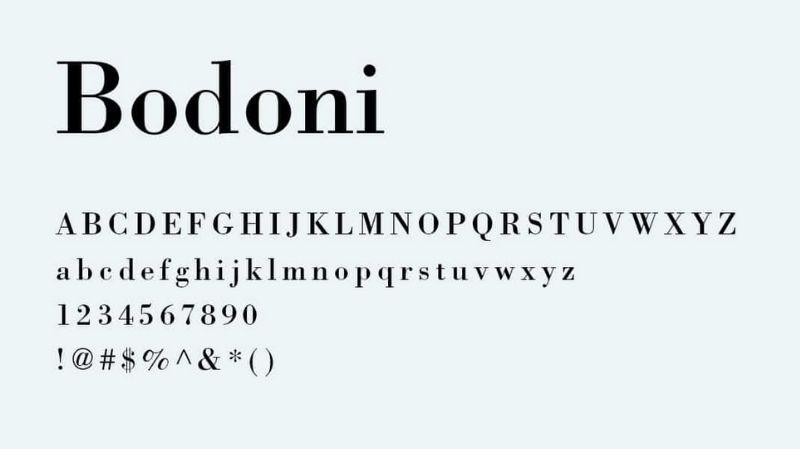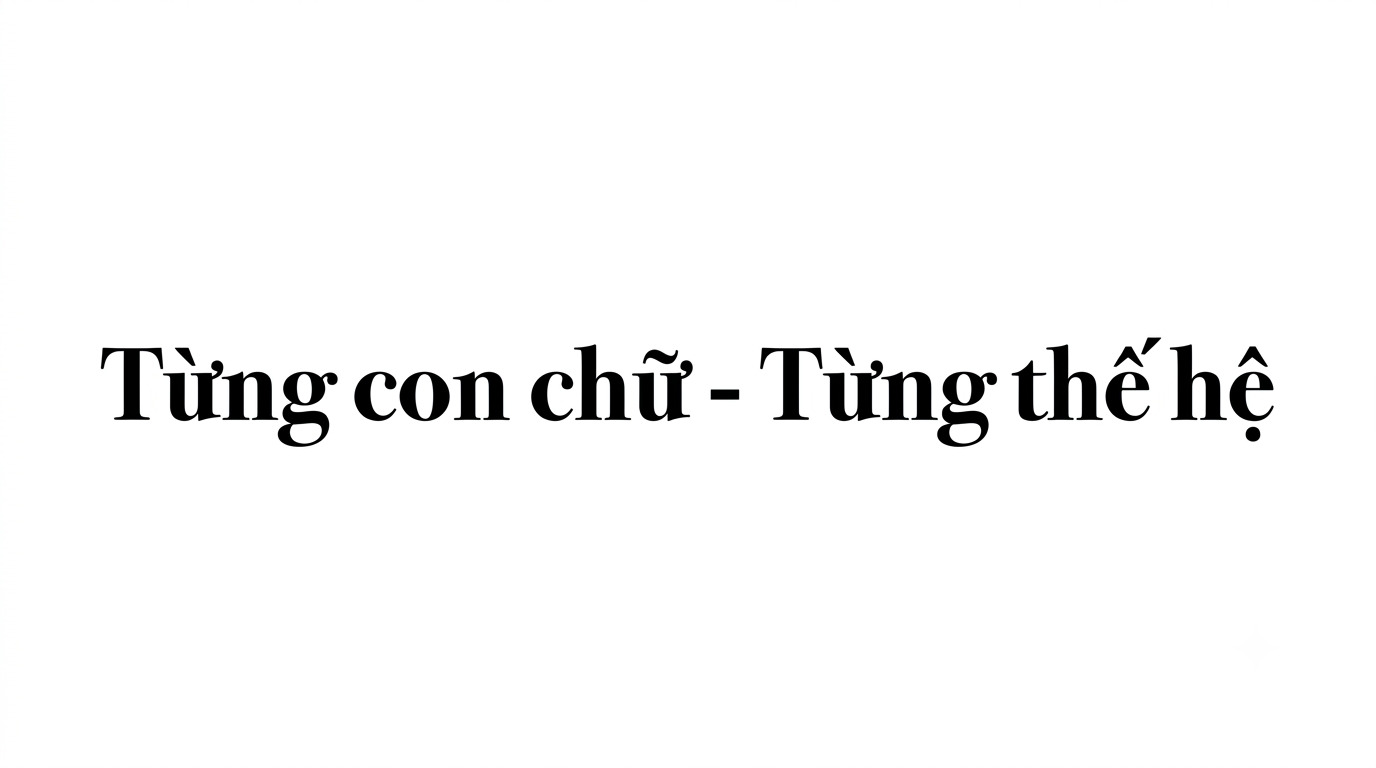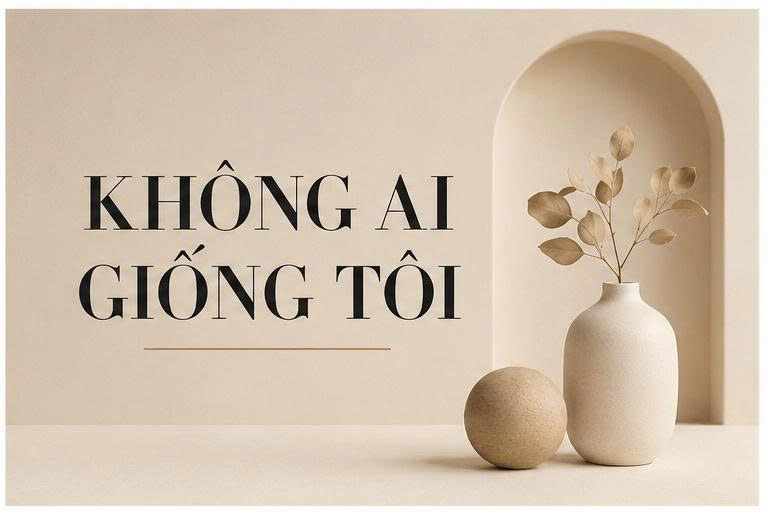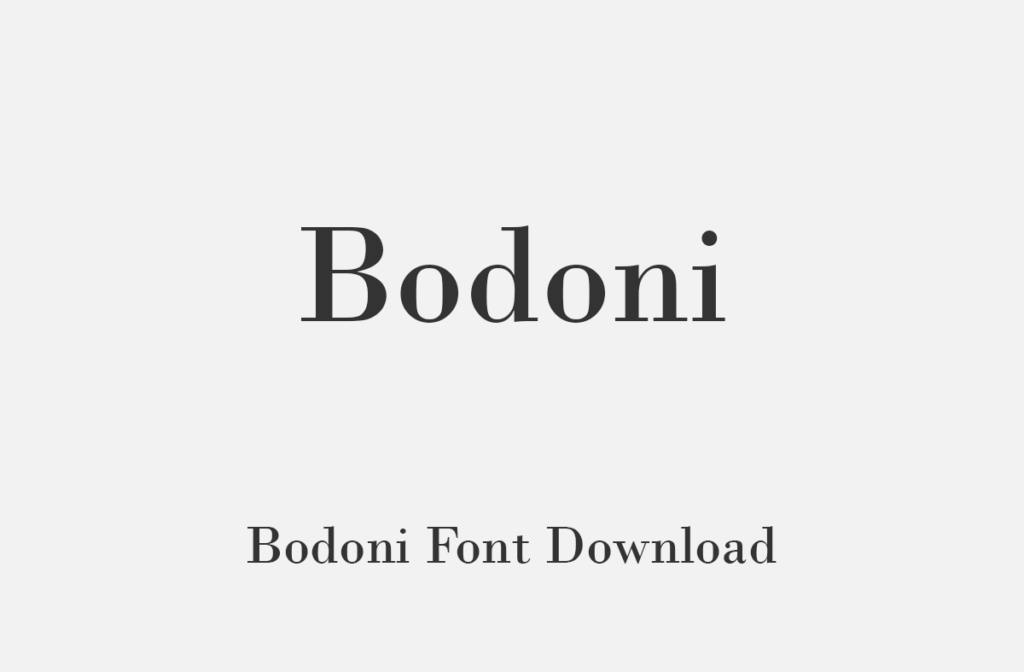
Font Bodoni Việt hóa là bộ phông chữ thuộc dòng Didone Modern Serif kinh điển do nghệ nhân in ấn Giambattista Bodoni sáng tạo tại Ý vào cuối thế kỷ 18, nổi danh toàn cầu với sự tương phản kịch tính giữa các thân chữ dày đậm và đường chân chữ mỏng manh như lưỡi dao cạo. Mang vẻ ngoài vương giả, uy nghiêm và đượm chất thời trang cao cấp, bộ font Bodoni Việt hóa là chất liệu trực quan tuyệt vời để các kiến trúc sư, nhà thiết kế kiến tạo phong thái sang trọng cho các bản vẽ phối cảnh biệt thự nghỉ dưỡng, sảnh đón tiếp khách sạn boutique hay bìa hồ sơ năng lực dự án.
Tỷ lệ tương phản cực độ và cấu trúc hình học của font Bodoni Việt hóa
Điểm cuốn hút của font Bodoni Việt hóa nằm ở cấu trúc hình học đứng thẳng tắp, các đường chân chữ nằm ngang phẳng lì không có góc bo chuyển tiếp (unbracketed serifs), tạo nên một hiệu ứng thị giác dứt khoát và thời thượng. Từng con chữ sở hữu những điểm nhấn hình giọt lệ tròn trịa ở các ký tự như ‘a’, ‘c’, ‘r’, tạo nên sự hòa quyện hoàn hảo giữa tính kỷ luật cơ học và nét duyên dáng tao nhã.
Sự ổn định về mặt thị giác của dòng font này tạo nên phong thái trang nhã, tin cậy và khẳng định vị thế đĩnh đạc của đơn vị kiến tạo. Khi xuất hiện trên các bề mặt vật liệu kiến trúc sang trọng như đá cẩm thạch trắng vân mây, inox mạ vàng xước mờ, kính phản quang hay gỗ mun trong các căn nhà lắp ghép cao cấp, Bodoni tạo nên điểm nhấn thị giác cuốn hút.
| Phân loại phong cách | Didone Modern Serif / High-contrast / Italian Classic |
| Các phân họ tiêu biểu | Bodoni MT, Bodoni Moda, Libre Bodoni, Bodoni 72 |
| Mục đích phù hợp | Biển tên villa cao cấp, bìa hồ sơ năng lực, logo |
Tư vấn từ chuyên viên: Bodoni sở hữu các nét thanh cực kỳ mỏng và độ tương phản lớn. Để bản thiết kế đạt hiệu quả thẩm mỹ tốt, bạn nên sử dụng phông chữ này cho các tiêu đề chính, tên dự án hoặc câu slogan ngắn ở kích thước lớn từ 20pt trở lên.
03 Ứng dụng Font Bodoni MT vào công trình thực tế
Nhờ vẻ ngoài quý phái và tính thẩm mỹ cao cấp, bộ phông chữ này mang lại giá trị thực tế lớn trong khâu tạo điểm nhấn cho các công trình hiện đại:
- Biển hiệu mặt tiền cho Villa và Boutique Homestay: Những nét chữ thanh lịch của Font Bodoni MT rất ăn ý khi gia công chữ nổi bằng inox vàng gương hoặc khắc chìm trên đá hoa cương, giúp căn nhà lắp ghép toát lên vẻ đài các và thu hút ánh nhìn của du khách.
- Bìa hồ sơ năng lực dự án kiến trúc: Sử dụng font Libre Bodoni Việt hóa cho tên dự án và tiêu đề các chương mục giúp hồ sơ trông như một ấn phẩm tạp chí kiến trúc danh giá, thể hiện gu thẩm mỹ tinh tế và năng lực của đơn vị kiến tạo.
- Hệ thống biển tên phòng và bảng chỉ dẫn nội khu: Phông chữ này khi in trên kính mờ hoặc kim loại phủ sơn tĩnh điện sẽ giúp không gian sảnh đón tiếp và hành lang toát lên chất nghệ thuật thanh lịch.
03 Lưu ý bố cục Bodoni Bold giữ trọn vẻ kiêu hãnh và rõ nét
Để khai thác hiệu quả vẻ đẹp của dòng font thời trang quý tộc này mà không làm ảnh hưởng đến khả năng đọc của bản vẽ, người thiết kế nên lưu tâm một số kinh nghiệm sau:
- Tránh sử dụng ở kích thước quá nhỏ: Do có các nét thanh mảnh như sợi chỉ, Bodoni Bold hiển thị đẹp nhất ở kích thước chữ từ trung bình trở lên trong in ấn. Ở kích thước quá nhỏ, nét thanh có thể bị mờ nhòe do độ mịn của chất liệu giấy in.
- Nới rộng khoảng cách ký tự: Đối với các tiêu đề viết hoa toàn bộ, việc kéo giãn nhẹ khoảng cách giữa các chữ cái sẽ làm tăng tính trang nghiêm, giúp bố cục thông thoáng và mang đậm phong thái kiến trúc đương đại.
- Bố trí nền màu đơn sắc tương phản: Bodoni phát huy hiệu quả thị giác cao khi đặt trên các nền màu đơn sắc có chiều sâu như đen tuyền, trắng ngọc trai, xám than hoặc xanh rêu sẫm, giúp các đường nét sắc sảo của bộ chữ được tôn vinh rõ ràng.